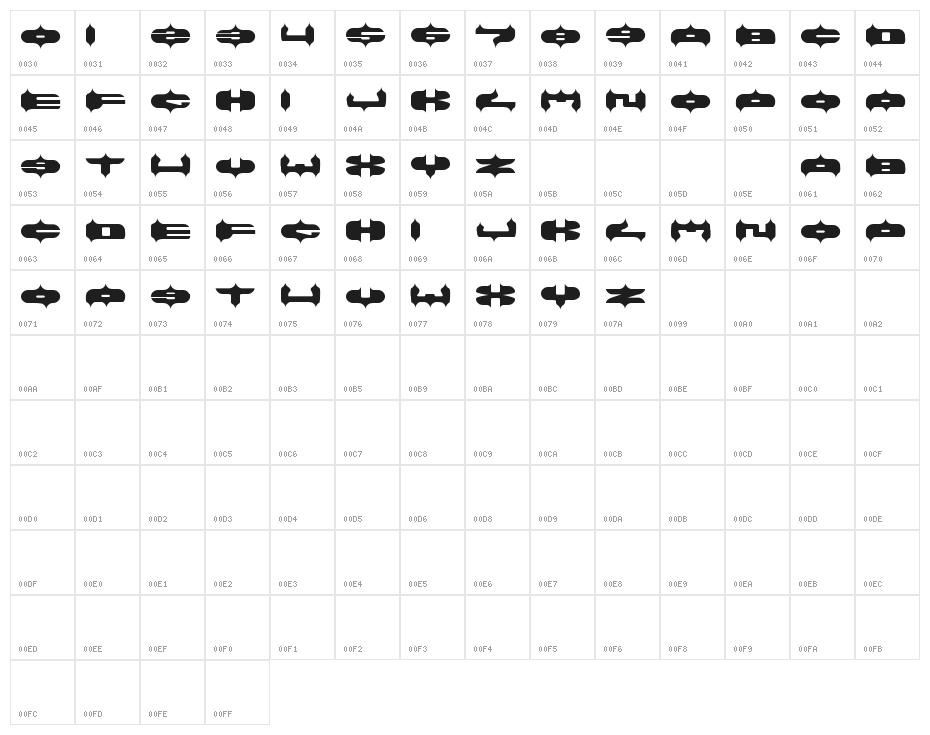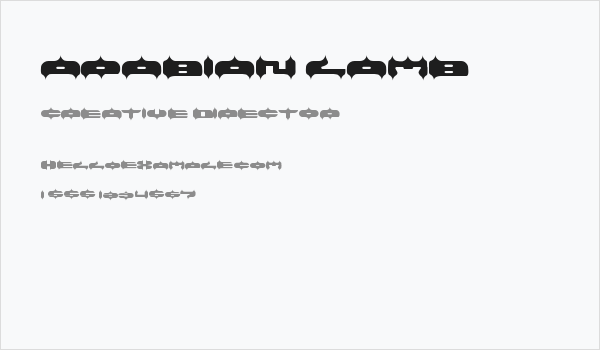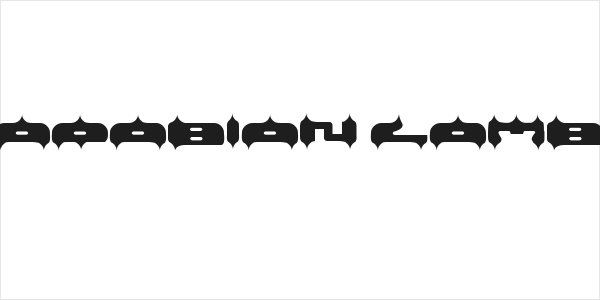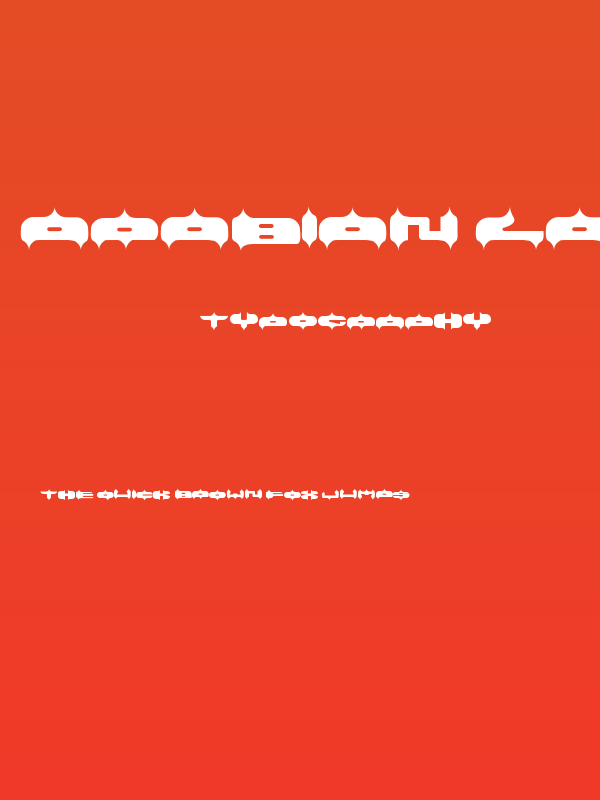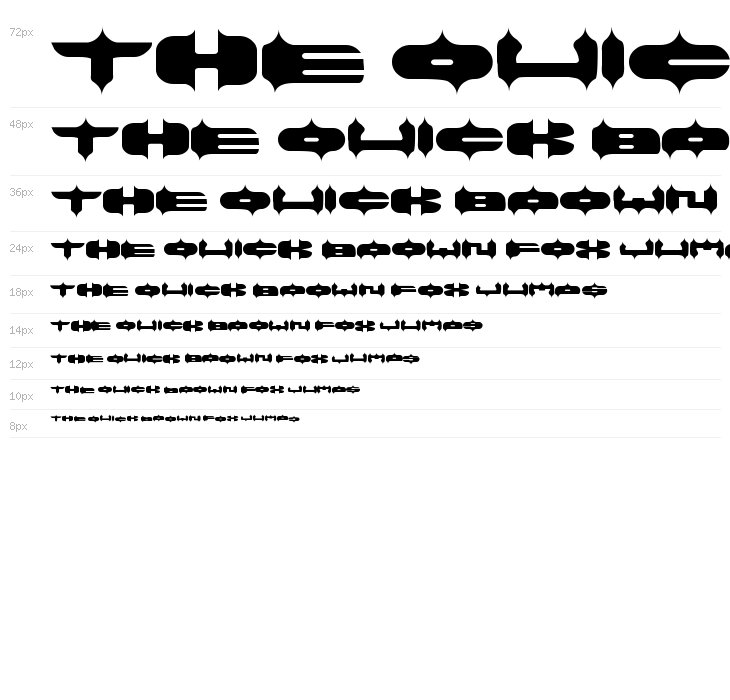
ARABIAN LAMB Font
| Progetti proposti | Ideal for branding, posters, event invitations, and cultural projects that require a unique and exotic aesthetic. |